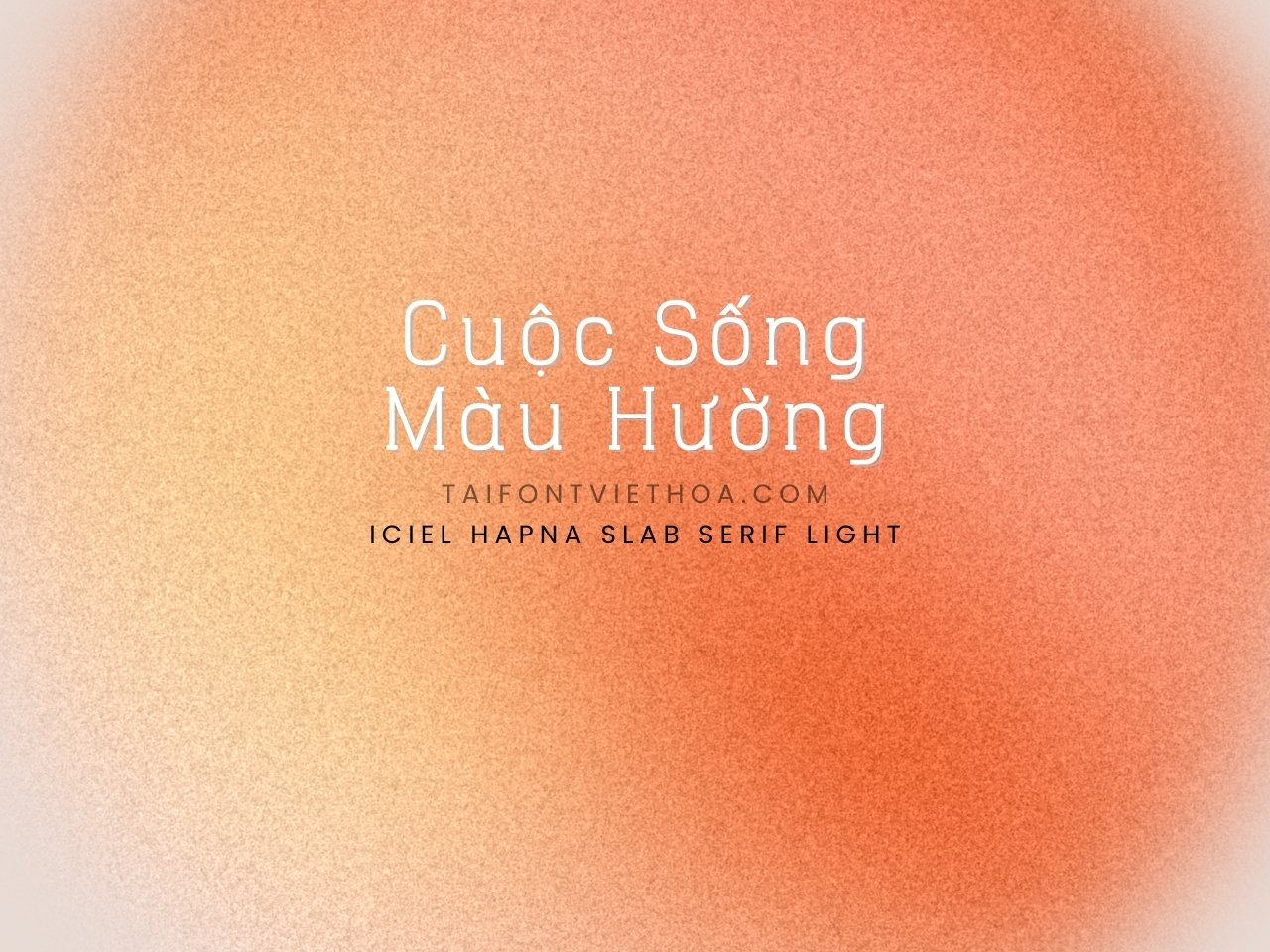
Giới thiệu về font iCiel Hapna Slab – Cứng cáp, hiện đại và đầy tính thương hiệu
iCiel Hapna Slab là một kiểu chữ slab serif hiện đại, được thiết kế với cấu trúc hình học rõ ràng và các đường nét chắc chắn. Đây là một dạng font chữ có chân mạnh mẽ, thích hợp cho các thiết kế đòi hỏi độ tin cậy và sự nổi bật. Phiên bản Việt hóa được thực hiện bởi iCiel, hỗ trợ tiếng Việt đầy đủ cùng hơn 60 ngôn ngữ khác, giúp font dễ dàng tích hợp vào các dự án đa ngôn ngữ và thương hiệu toàn cầu.
Font đã được taifontviethoa.com chọn lọc và sưu tầm kỹ lưỡng nhằm đáp ứng nhu cầu thiết kế logo, tiêu đề, bảng hiệu và các ứng dụng branding chuyên nghiệp. Với vẻ ngoài mạnh mẽ, chuyên nghiệp và giàu cá tính, iCiel Hapna Slab mang lại hiệu quả truyền thông cao cho các doanh nghiệp trong lĩnh vực công nghệ, bất động sản, truyền thông hoặc giáo dục hiện đại.
Đặc điểm thiết kế và ứng dụng nổi bật của font iCiel Hapna Slab
Hapna Slab được xây dựng trên nền tảng hình học với các chân chữ vuông vắn, độ dày nhất quán và chiều cao chữ hợp lý. Kiểu chữ này mang đến sự chắc chắn, dễ đọc và hiệu quả khi dùng ở kích thước lớn. Thiết kế slab serif giúp tạo cảm giác chuyên nghiệp, ổn định, trong khi các chi tiết bo góc nhẹ mang lại cảm giác thân thiện và linh hoạt hơn trong ứng dụng thực tế.
iCiel Hapna Slab phù hợp với nhiều ngành nghề như công nghệ, giáo dục, bất động sản, startup, báo chí hoặc thương hiệu cá nhân. Một số ứng dụng tiêu biểu gồm: thiết kế logo, tiêu đề sách, bìa tạp chí, giao diện app, infographic chuyên môn, banner quảng cáo hoặc bảng hiệu doanh nghiệp. Đây là lựa chọn lý tưởng cho những thiết kế cần sự hiện đại, rõ ràng và đáng tin cậy.